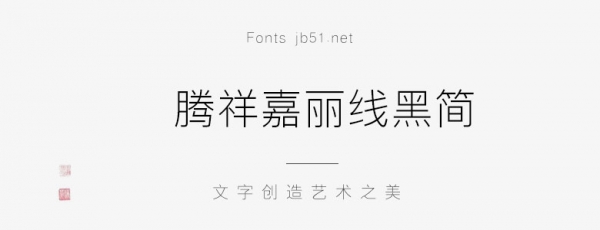
騰祥嘉麗線黑簡(jiǎn)是一款不錯(cuò)的藝術(shù)字體,由騰祥字庫(kù)出品,該字體字型端正,重心平穩(wěn),布白均勻,適合應(yīng)用于藝術(shù)設(shè)計(jì)、平面宣傳設(shè)計(jì)、網(wǎng)頁(yè)設(shè)計(jì),書(shū)法字帖等領(lǐng)域,需要的朋友可以前來(lái)本站下載。
騰祥嘉麗黑體系列字庫(kù)為騰祥公司早期自行開(kāi)發(fā)的傳統(tǒng)黑體字庫(kù)。字體風(fēng)格采用橫豎筆畫(huà)無(wú)襯線裝飾的設(shè)計(jì),融入英文設(shè)計(jì)元素。字型端正,重心平穩(wěn),布白均勻。此款字體為騰祥嘉麗黑體系列中纖細(xì)一款,橫豎筆畫(huà)等粗,